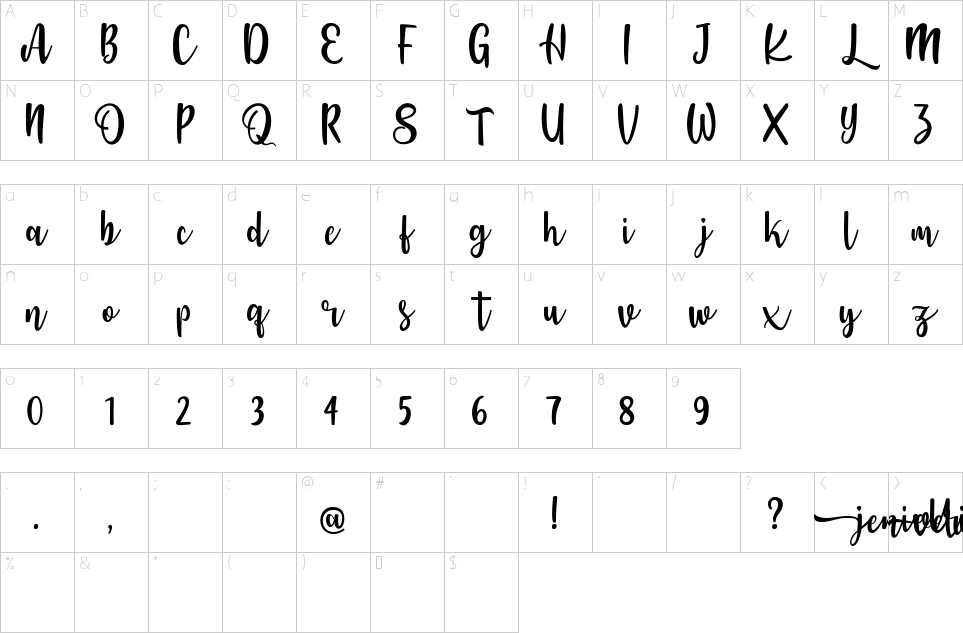
A Jennifer Ellis Font oferece uma beleza minimalista e elegante, perfeita para qualquer projeto de design, seja em design de sites, gráficos publicitários ou até mesmo em textos de e-mail. Desenvolvida pela OCS Studio, esta fonte é ideal para designers que valorizam a simplicidade e elegância em seus projetos. Com um design arquitetônico, a Jennifer Ellis captura a essência da simplicidade, oferecendo uma ótima opção para quem busca um estilo limpo e confiável. Ainda não experimentou a Jennifer Ellis Font? Faça seu download agora e descubra como essa fonte pode enriquecer seus projetos. Com 10.321 downloads, ela é uma fonte que merece espaço no seu portfólio de recursos gráficos.